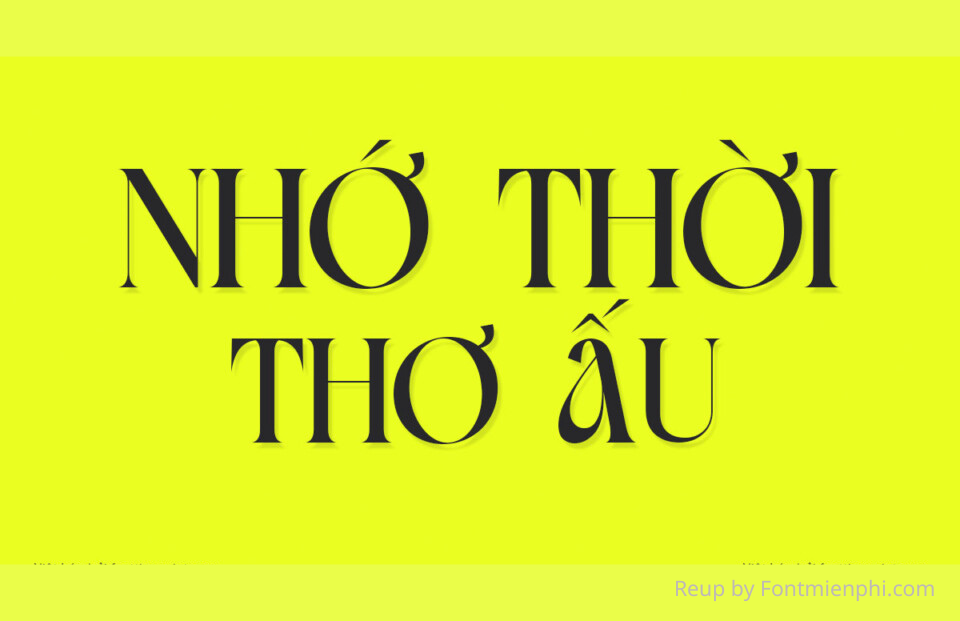
1FTV VIP Moves Cabse – Chuyển động phá cách, đậm chất riêng
hám phá ngay font việt hóa 1FTV VIP Moves Cabse độc đáo tại Font Chữ Việt (fontchuviet.com). Sở hữu đường nét uyển chuyển, phá cách và được tối ưu dấu tiếng Việt chuẩn xác, phông chữ này là lựa chọn hoàn hảo cho các thiết kế poster, banner và nghệ thuật typography sáng tạo.
1FTV VIP Moves Cabse là một trong những phông chữ mang đậm tính nghệ thuật và sự linh hoạt, nay đã được việt hóa hoàn chỉnh và chia sẻ miễn phí tại Font Chữ Việt (fontchuviet.com). Nếu bạn đang tìm kiếm một kiểu chữ để làm nổi bật thông điệp, phá vỡ sự nhàm chán và tạo hiệu ứng thị giác mạnh mẽ, đây chắc chắn là một “vũ khí” thiết kế không thể bỏ qua.
Điểm nhấn của 1FTV VIP Moves Cabse nằm ở những đường nét chuyển động vừa uyển chuyển, nhịp nhàng lại vừa hiện đại, dứt khoát. Phông chữ này phát huy sức mạnh tối đa khi được ứng dụng vào các dự án yêu cầu tính sáng tạo cao như: thiết kế logo, poster sự kiện âm nhạc/nghệ thuật, banner quảng cáo, tiêu đề (heading) tạp chí, bao bì sản phẩm hay các ấn phẩm truyền thông trên mạng xã hội.
Đặc biệt, phiên bản việt hóa được cung cấp bởi Font Chữ Việt đã được chăm chút kỹ lưỡng về mặt kỹ thuật. Từng dấu câu (hỏi, ngã, nặng…) được tinh chỉnh để tạo ra sự hài hòa với bộ ký tự gốc, đảm bảo không xảy ra tình trạng lỗi font, gãy nét hay lệch khoảng cách khi bạn gõ văn bản tiếng Việt trên bất kỳ phần mềm thiết kế nào như Photoshop, Illustrator hay Figma.